Eメールマーケティングに最適なフォントを選択する方法:簡潔なガイド
公開: 2019-05-28ウェブサイト、メール、広告など、オンラインで顧客や見込み客とコミュニケーションをとることを考えると、基本的には、言葉、画像、色など、サービスを提供するのに役立つツールがいくつかあります。点。 しかし、一般的にそれに値する注目を集めない重要なツールの1つは、使用するフォントまたはタイポグラフィです。 フォントは視覚的な心理的意味を持ち、読者があなたのコンテンツをどのように認識するかに大きな影響を与えます。
電子メールに関しては、適切なフォントを選択するのはマーケティング担当者の責任です。 これは、電子メールフォントが何を伝えているかだけでなく、オペレーティングシステムや電子メールクライアントでのフォントの可用性の問題も関係しているためです。 それは、あなたがよく理解して選択したフォントがどのようにレンダリングされるか、そしてあなたの電子メール購読者が彼らの電子メールで最終的に見るか見えないかについてです。 このブログ投稿では、メールマーケティングのフォントについて、タイプ、レンダリングの問題、フォールバックなど、すべてを学びます。
メールで使用されるフォント
マーケターやデザイナーがメールで使用するフォントはたくさんありますが、各文字のモデル化方法に基づいて、次の4つのファミリに分けることができます。
- セリフ
- サンセリフ
- 筆記体
- モノスペース
セリフフォント
読みやすいと考えられているセリフフォントは、一般的に電子メールで使用されます。 間隔の広い文字は、ストロークの端で繁栄し、ストロークの軸は通常、左に傾いています。 最も人気のあるセリフフォントはGeorgiaとTimesNewRomanです。
セリフフォントは、読者に実用的な洞察を提供するコンテンツに最適です。 これらのフォントは、製品やサービスの利点を示すためにも使用できます。
Publican Ankerによるこのメールは、Times New Romanを使用して、予約の確認に関するメールを正式に確認しています。 この電子メールフォントは、優れた読みやすさも保証します。
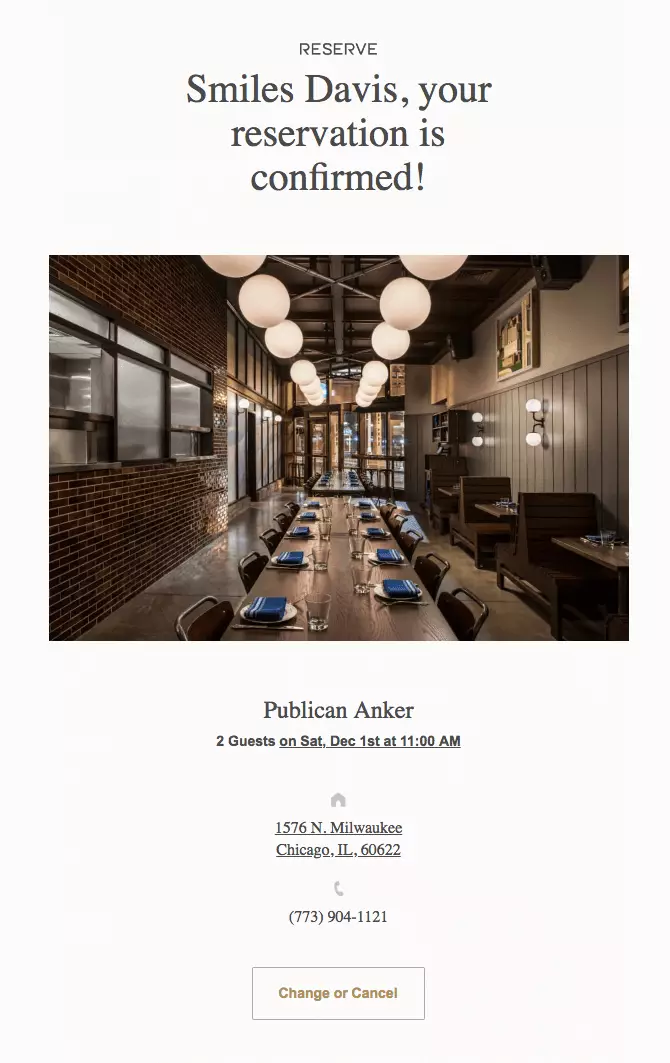
サンセリフフォント
繁栄のないセリフフォントは、サンセリフフォントに取って代わられます。
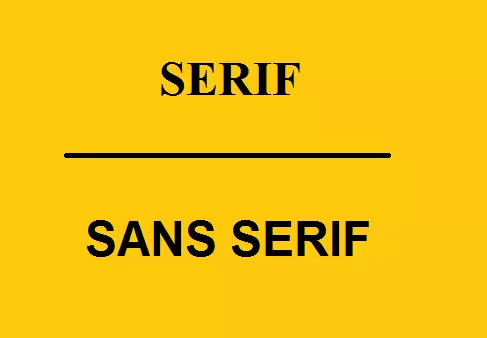
すべての文字に装飾的なストロークがないため、このフォントは非常にセミフォーマルな外観になっています。 このファミリで最も人気のあるフォントは、Arial、Trebuchet MS、Verdana、Open Sans、およびHelveticaです。
サンセリフフォントは、電子メールが簡単に書かれたコンテンツセクションで構成されている場合に一般的に使用されます。
Facebookによるこのメールは、彼らが使用したArialフォントで素晴らしい印象を与えます。
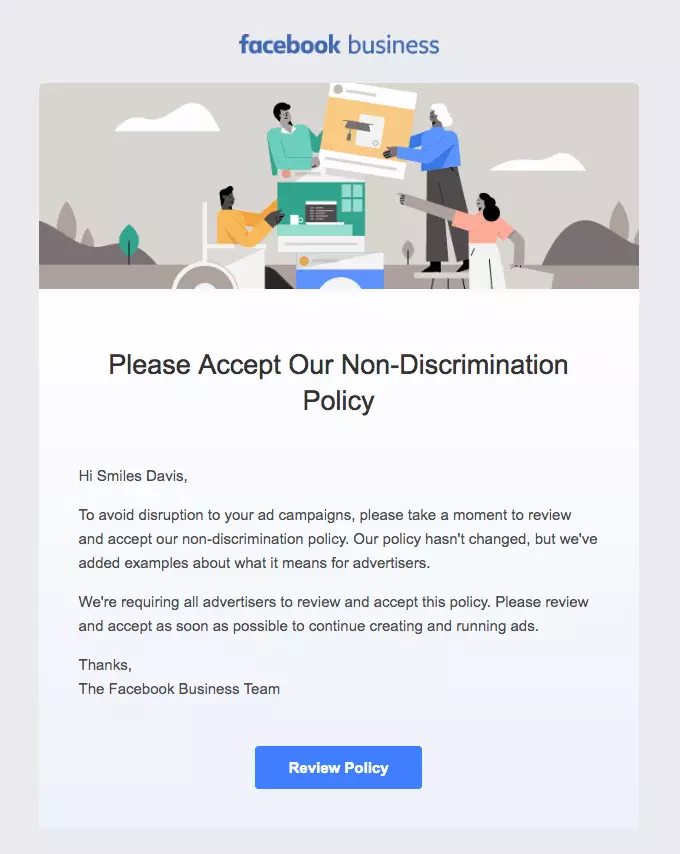
書道フォント
スクリプトスタイルと流れるような動きを使用して手書きの単語の外観をエミュレートする書道フォントは、非常に芸術的です。 書道は、西洋、東洋、またはアラビア語であり、それぞれが異なる地域の言語を反映しています。 ただし、デジタル画面で読むと目にはそれほど簡単ではないため、電子メールのコピーではあまり使用されません。 あなたは注意を引くために電子メールの見出しでそれらを見つけるでしょう。
読者は派手なフォントを読むのに86%長い時間がかかるため、これらのフォントを賢く使用することが重要です。
このメールでは、Simpleは書道フォントを使用して手書きの単語の感触をもたらし、メールを読みやすくしています。
MACがシンプルなフォントと芸術的なフォントを組み合わせて、ウェルカムメールで読者の注意を引く方法をご覧ください。
等幅フォント
タイプライターフォントに似ており、モノスペースフォントの文字の最後にはブロックがあります。 このフォントは、電子メールにまばらで最小限の感触を与える場合に最適です。 Courier、Lucida Console、およびMonacoは、このファミリに属するフォントの一部です。
Misfitによるこのメールをチェックしてください。 このメールでは、Andale Mono、Lucidaコンソール、Courierなど、さまざまなモノスペースフォントを組み合わせて使用しています。
WebセーフフォントまたはWebフォント—それはどのように重要ですか?
Webセーフフォントは、ほぼすべてのオペレーティングシステムで正しくレンダリングされるフォントです。 それらには、Arial、Comic Sans、Courier New、Georgia、Impact、Palatino、Tahoma、Trebuchet MS、Times New Roman、Verdanaなどのフォントが含まれます。
一方、Webフォントは、複数のオペレーティングシステムやデバイスにはありません。 さらに、すべての電子メールクライアントがそれらを表示するわけではありません。 Webフォントをサポートする電子メールクライアントは次のとおりです。
- ネイティブAndroidメールクライアント。
- Outlook 2000;
- Outlook.comアプリ;
- AOLメール;
- Apple Mail;
- iOSメール;
- Safariブラウザ。
したがって、これらのフォントにはフォールバックを使用することが不可欠になります。 Webフォントは、電子メールクライアントがダウンロードしてサブスクライバーの電子メールに表示するサーバーでホストすることもできます。
一部のデザイナーはカスタムフォント用のものを持っています。 これらも、すべてのシステムと電子メールクライアントでレンダリングするためにフォールバックが必要です。 常にメールをテストして、フォントの適切なレンダリングとフォールバックを確認してください。
フォールバックの選択
では、メールフォントのフォールバックをどのように選択しますか? これらの要因はあなたを助けます:
フォントサイズ
フォントが異なれば高さも異なります。 したがって、特定のフォントのフォールバックを選択するときは、選択するフォントが元のフォントよりも短くも高くもないことを確認してください。
間隔
フォールバックフォントの文字間の間隔が、電子メールで使用しているフォントの間隔と同じであることを確認してください。 そうでない場合は、各単語の長さを増減できます。
電子メールでHelveticaを使用することを選択し、電子メールサブスクライバーがAppleデバイスを持っているとします。 あなたが作成したのと同じように、Helveticaであなたのメールが表示されます。 ただし、Windowsユーザーがデバイスで電子メールを開くと、コードに追加した最初のフォールバックが表示されます(Verdanaなど)。 それも利用できない場合は、ユーザーは、あなたが言及した3番目のオプション、または利用可能なサンセリフフォントのフォントを表示します。 だから、これがどうなるかです—カスタムフォント->ウェブセーフフォント->システムフォント。
Eメールマーケティングに最適なフォントの色
フォントの色は、メッセージを目立たせるのに役立ちます。 ただし、色の使用を制限することが最善のオプションです。 3つが制限です。1つはヘッダー用、1つは残りのテキスト用、もう1つはリンクを強調表示するためのものです。
また、選択する色は、背景色とのコントラストが十分に高く、読みやすさが向上している必要があります。
まとめ
次のEメールマーケティングキャンペーンに最適なフォントを選択する準備が整ったときに役立つ「Eメールのタイポグラフィ」のヒントをいくつか紹介します。
- あなたのEメールに適したフォントを選択してください— ComicSansのビジネスEメールはあなたに不利に働きます。
- ブランドイメージを構築するために、フォントタイプとフォントカラーをブランドカラーと組み合わせて使用します。
- 電子メールでは、標準の行間隔(フォントサイズの1 1/2サイズ)を維持します。
- メールフォントを読みやすくします—小さすぎたり大きすぎたりしないでください。
- 電子メールで使用するフォントの種類と色を2つに制限します。
- カスタムフォントにフォールバックフォントを追加することを忘れないでください。
- フォールバックを賢く選択します。 文字間の高さと間隔が重要です。